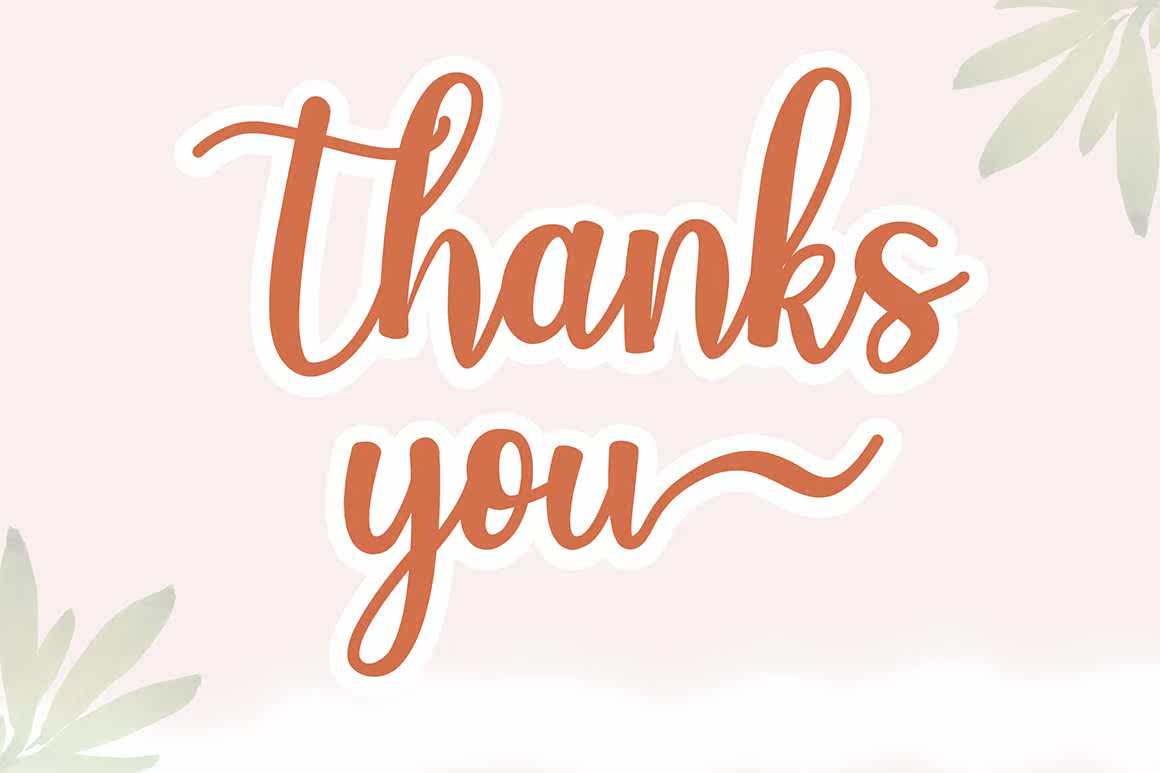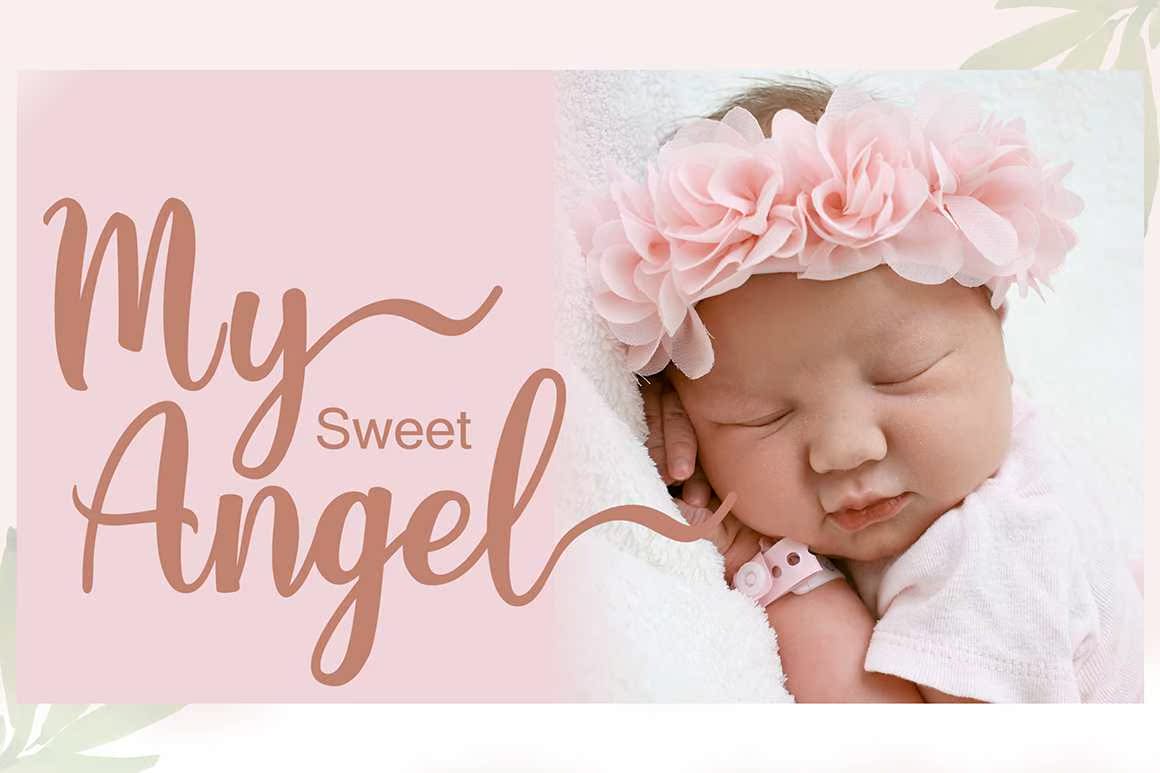
Revaniaisa Modern CaligraphyScript字体,使用毛笔创建。使用可应用于所有小写字母结尾的单独基线跳舞。使用纸张进行打印。扫描、矢量化并仔细设计。Revania包括连接、替换和对大多数西方语言的国际支持。Revaniaisa Modern CaligraphyScript字体,使用毛笔创建。使用可应用于所有小写字母结尾的单独基线跳舞。在纸上进行了打印。扫描、矢量化并小心地进行了修改。修订内容包括连字、替换和对大多数西方语言的国际支持。